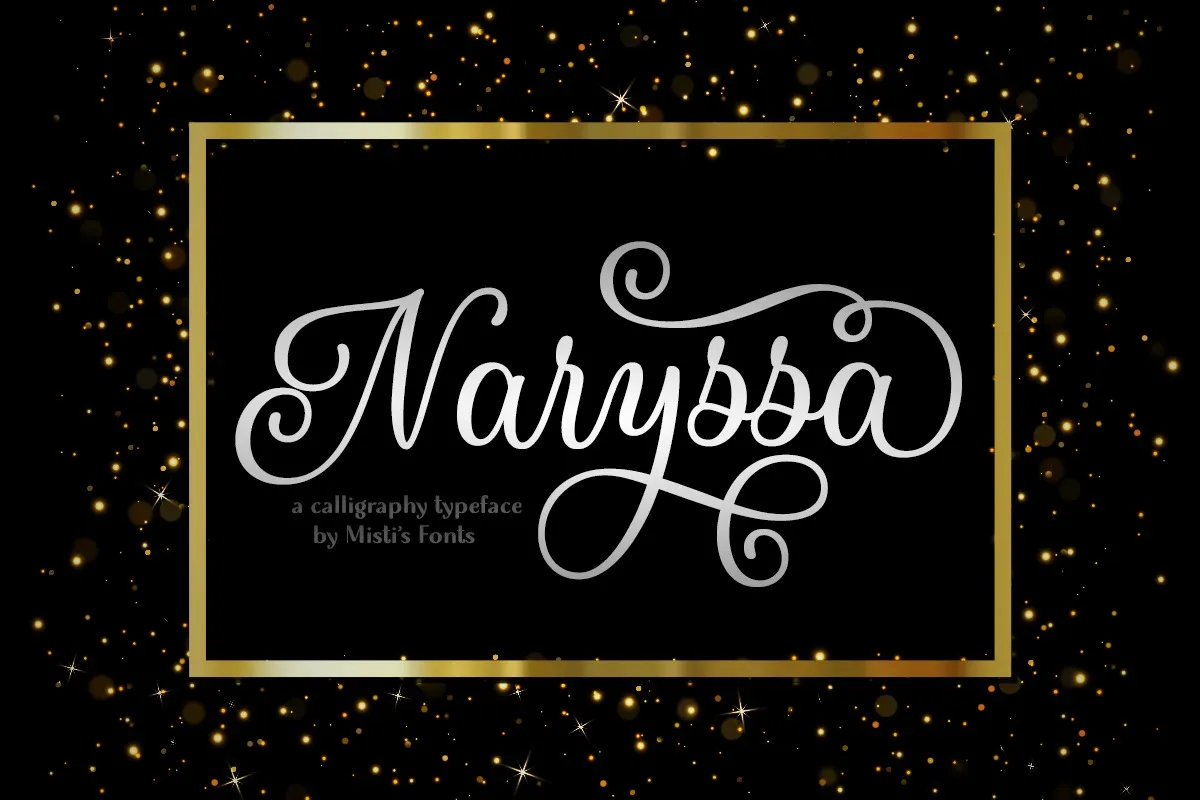
Naryssa Font – Download Grátis
A Naryssa Font é uma linda fonte tipográfica que oferece uma aparição vibrante e deslumbrante à sua escrita. Desenvolvida pelo designer Misti’s Fonts, ela foi criada com muita habilidade para manter-se fresca e atraente. Este tipo de font é ideal para quem busca dar um toque único aos projetos mais criativos. Naryssa é uma fonte de calligrafia que se destaca por sua versatilidade e facilidade de uso. Ela está codificada PUA, o que significa que você pode acessar todos os caracteres e as curvas de formação com grande facilidade, permitindo-lhe experimentar diferentes estilos em seus projetos. Quer seja para criar algo inovador ou apenas dar um toque especial à sua mensagem, Naryssa está aqui para ajudá-lo. Seja em uma newsletter, em um livro de arte, em seu site pessoal ou qualquer outro projeto visual que você esteja trabalhando, a Naryssa vai garantir que o seu design brilhe na multidão. Descubra como ela pode dar vida à sua criatividade!